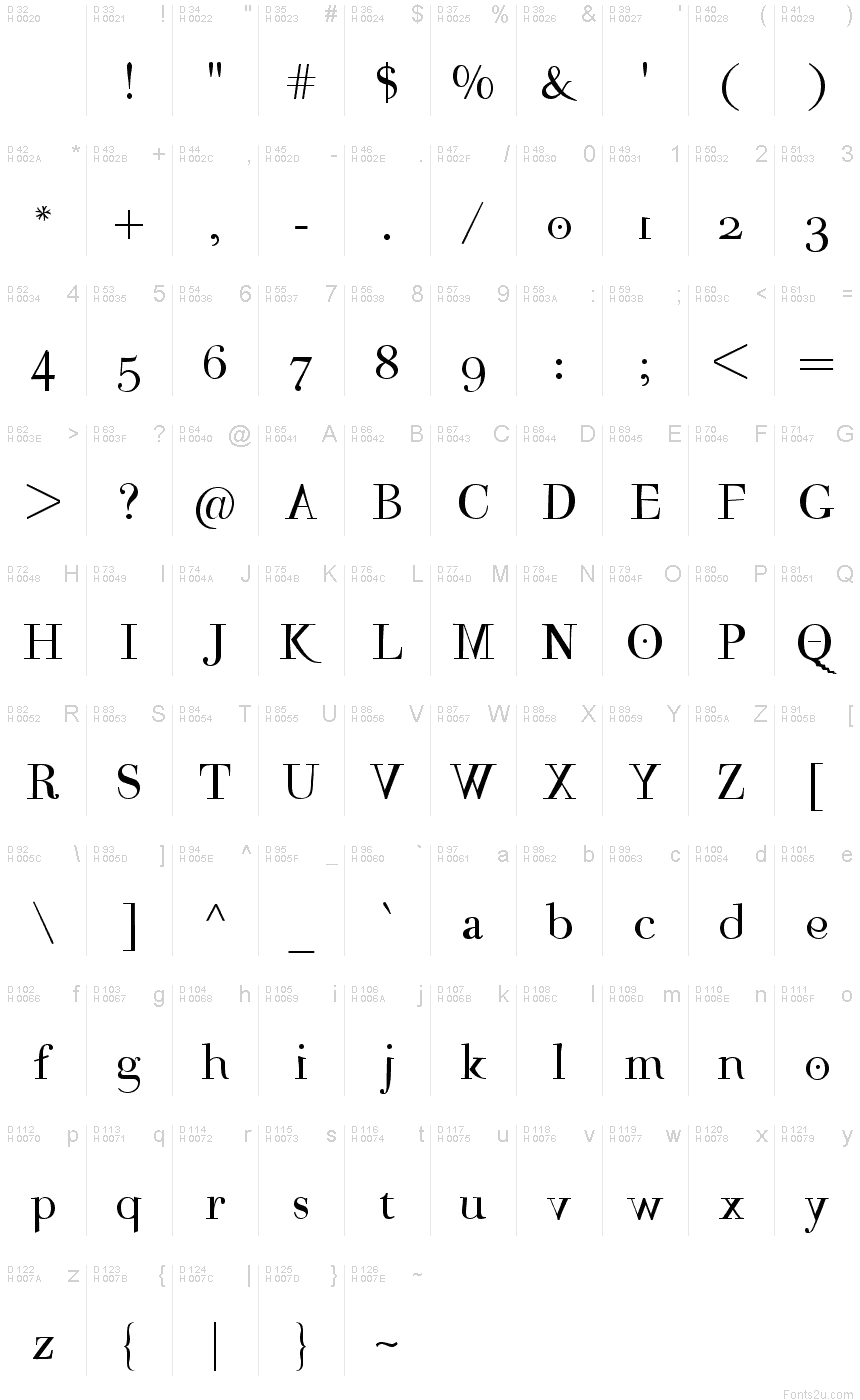
Mutoni to darmowy szeryfowy krój akcydensowy w stylu retro, z wysokimi, eleganckimi literami i wyraźnym kontrastem między grubymi a cienkimi elementami. Cienkie włoskowate linie i szerokie pociągnięcia pionowe przywodzą na myśl eleganckie reklamy z połowy XX wieku.
Opakowania modowe oraz okładki wydawnicze pasują do jego wyrafinowanego, lekko teatralnego charakteru. Może również nadawać identyfikacji wizualnej restauracji lub plakatom imprezowym formalny wygląd z nutą minionej epoki. W projektach opartych na obrazach płynne krzywe i wyraźne szeryfy mogą nawiązywać do szkła koktajlowego, fałd tkanin lub opływowych detali architektonicznych.